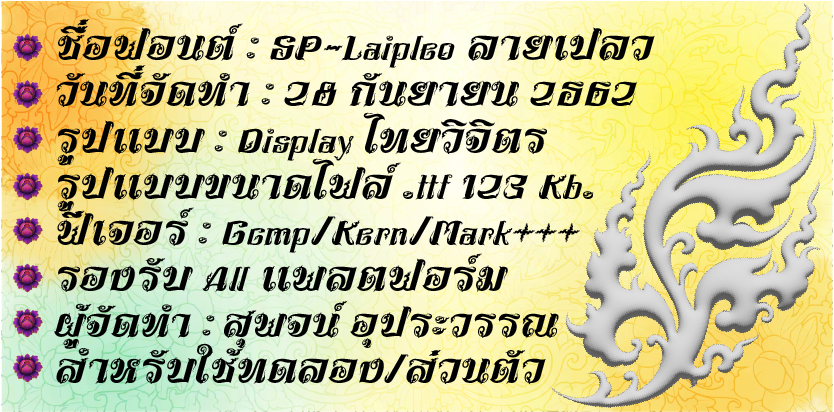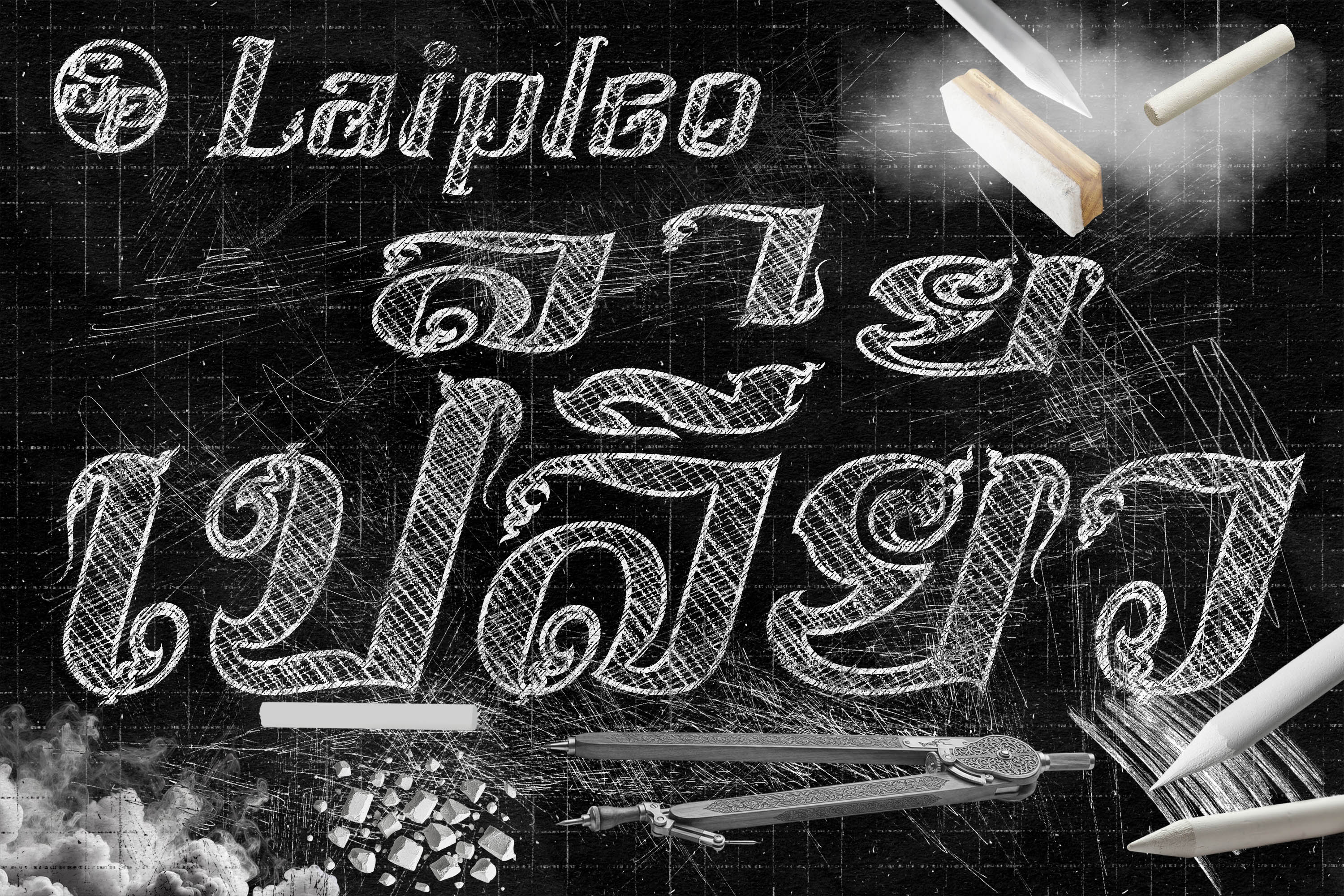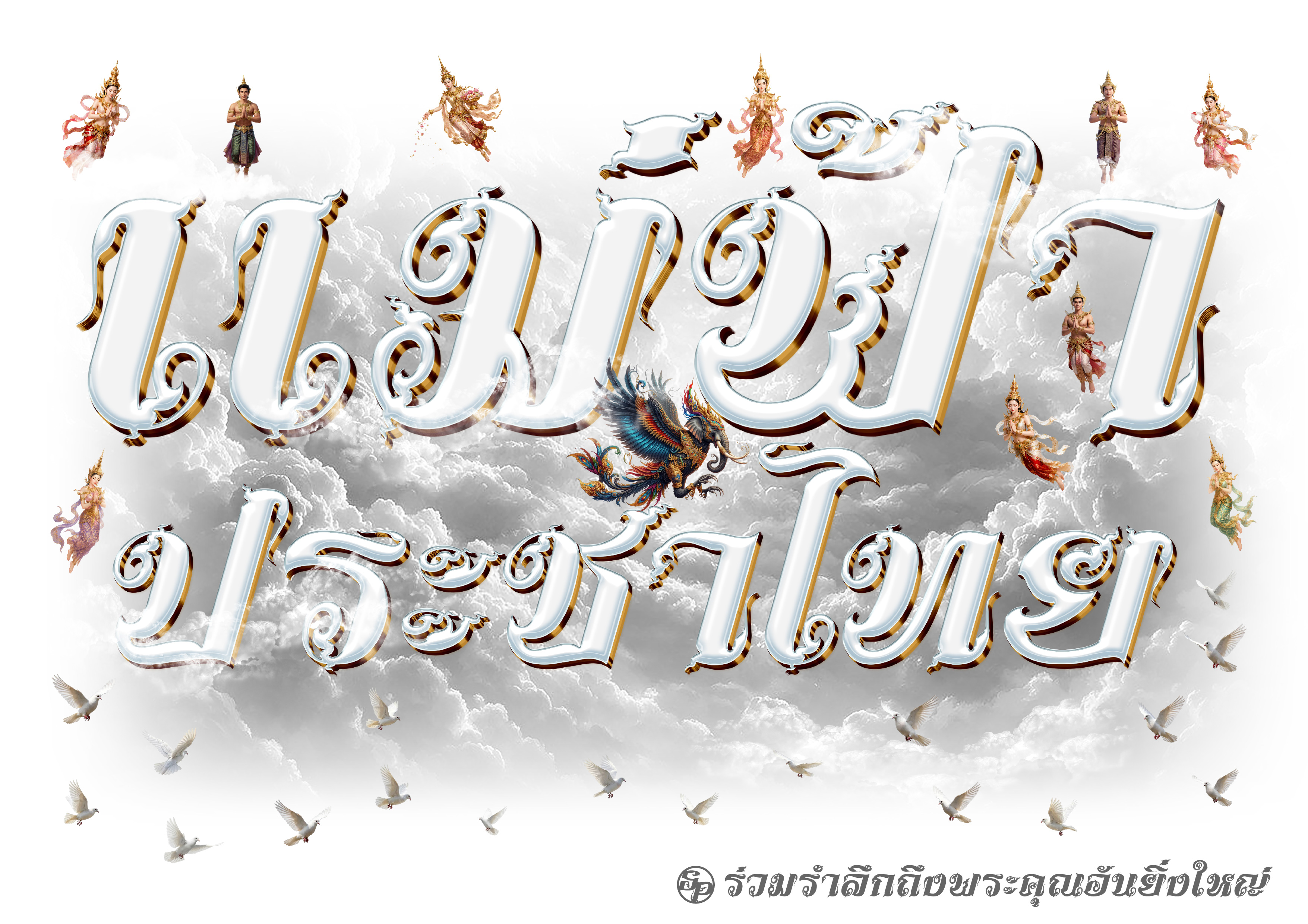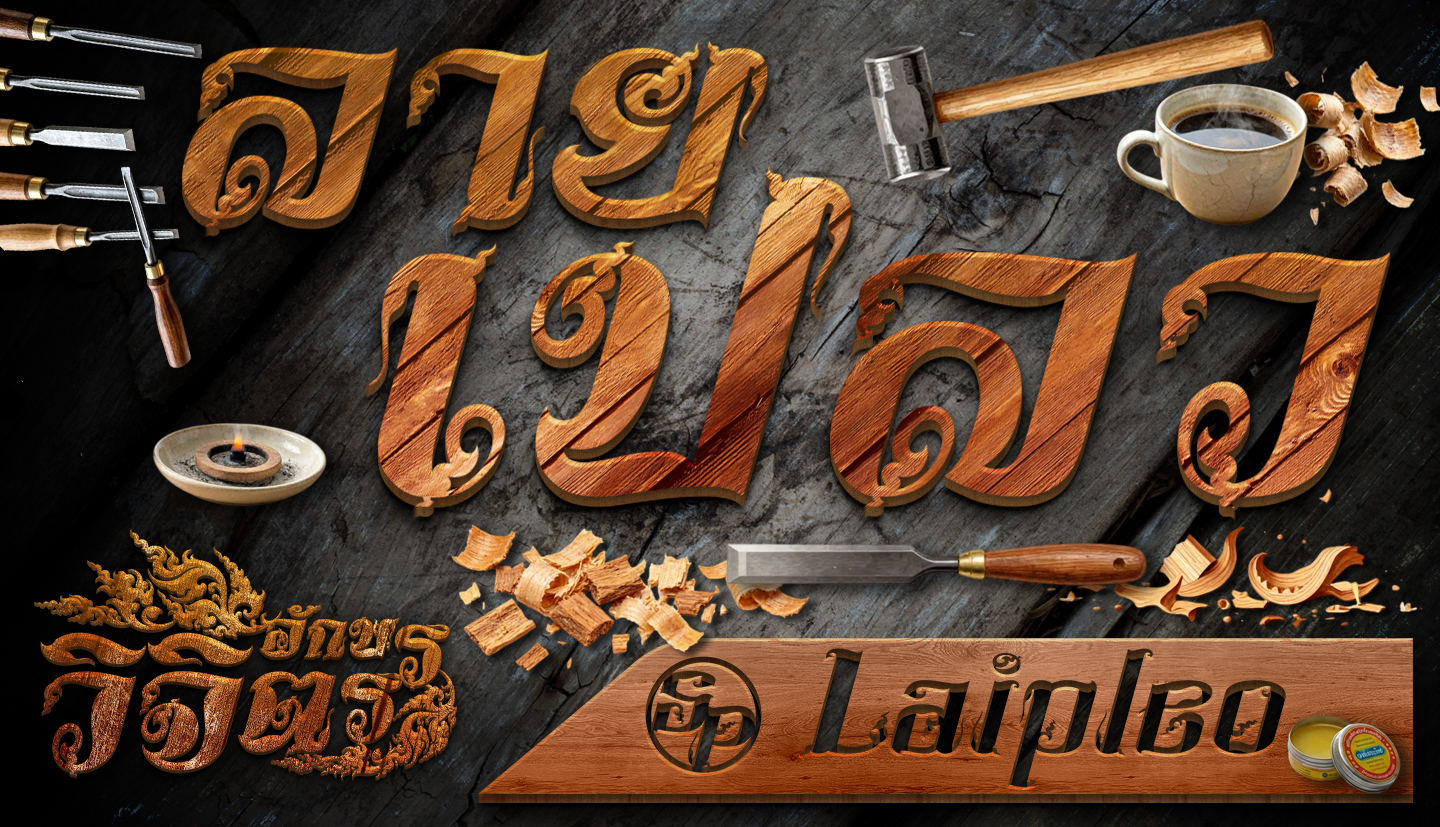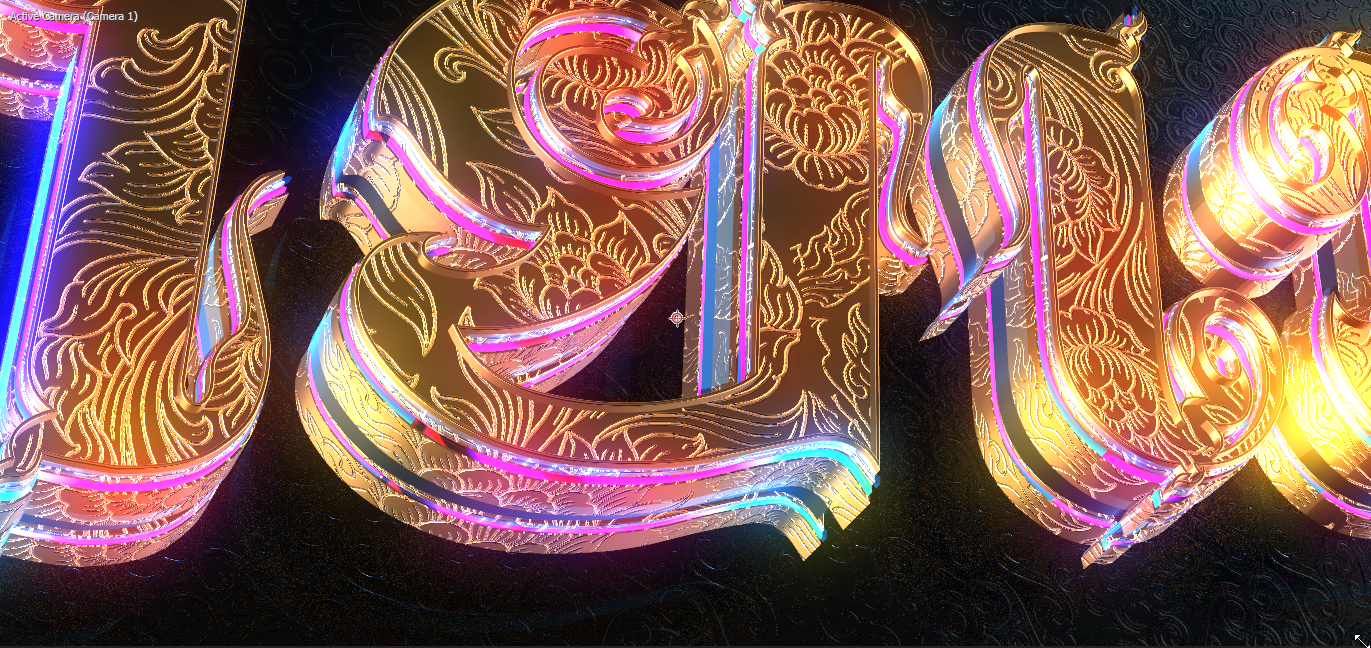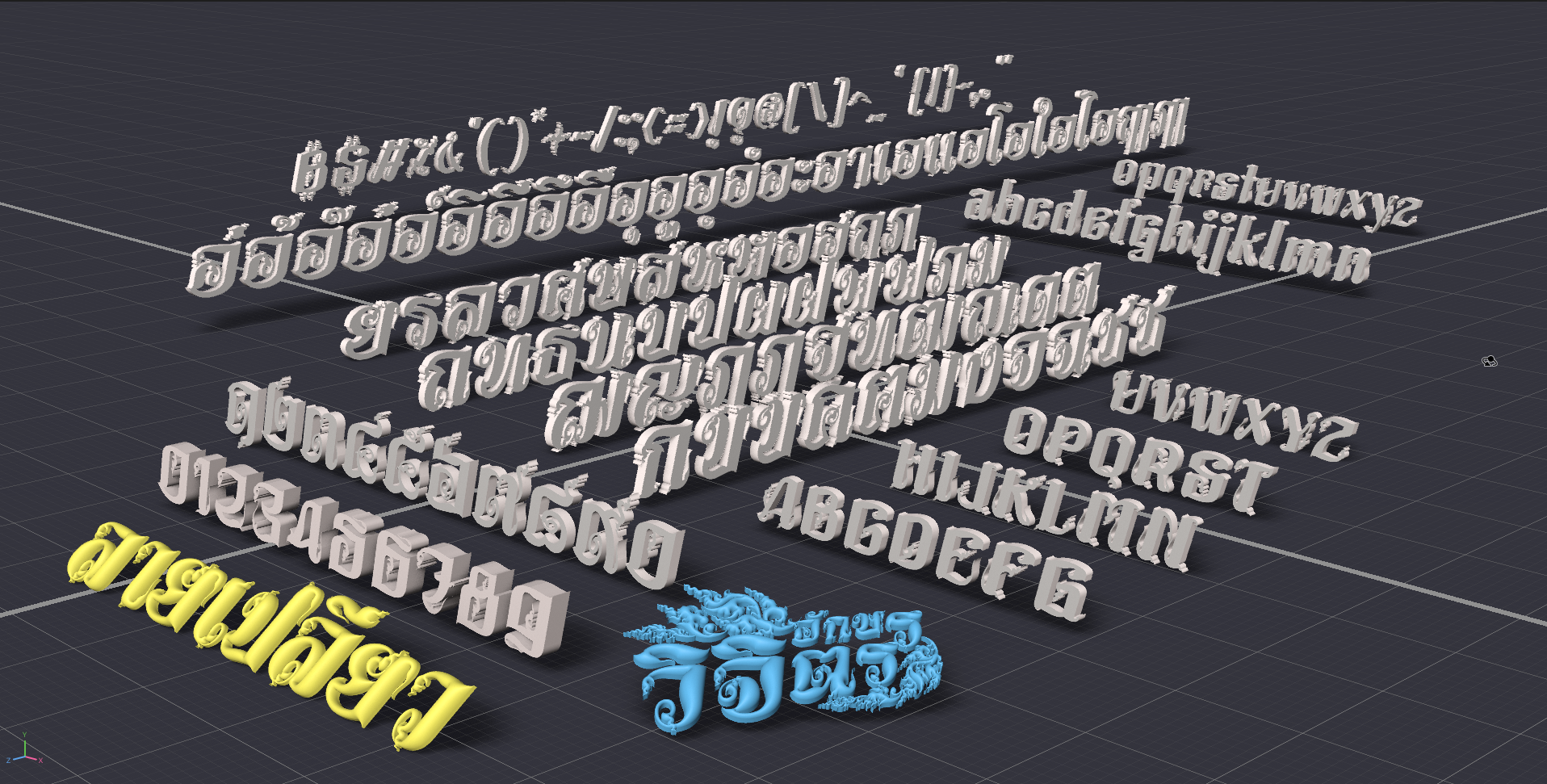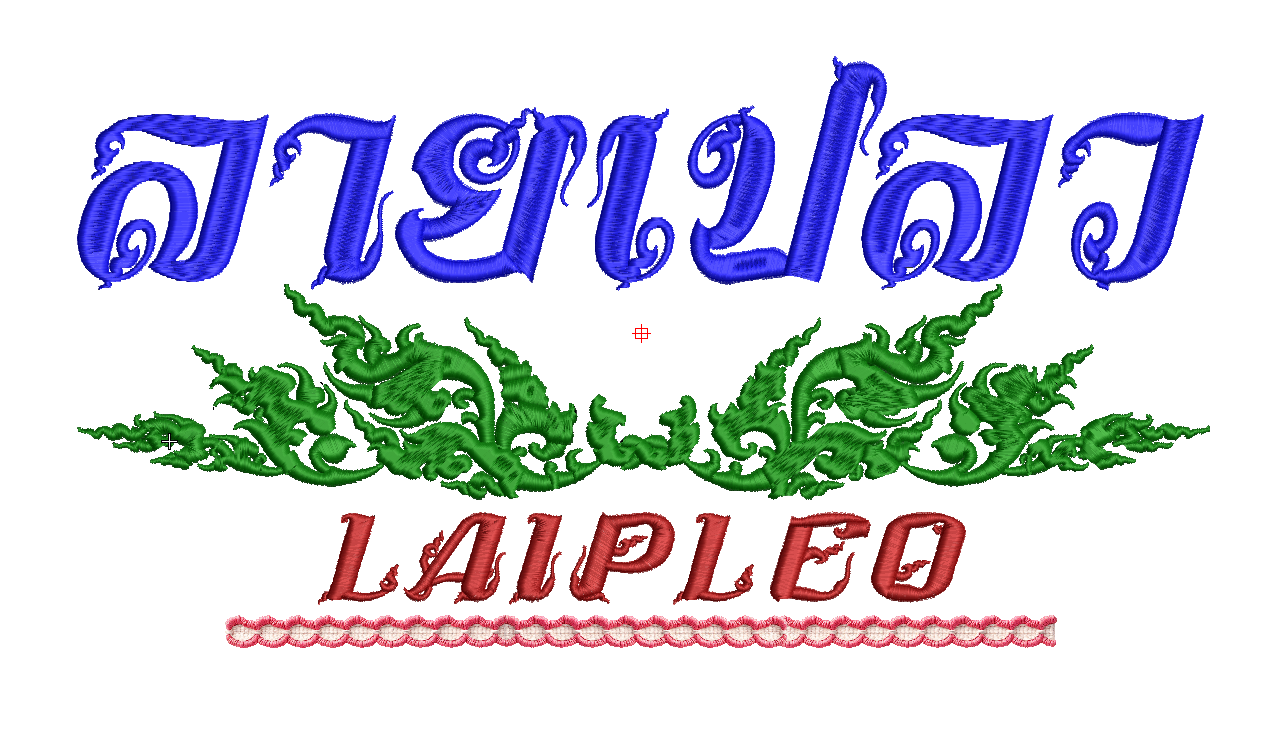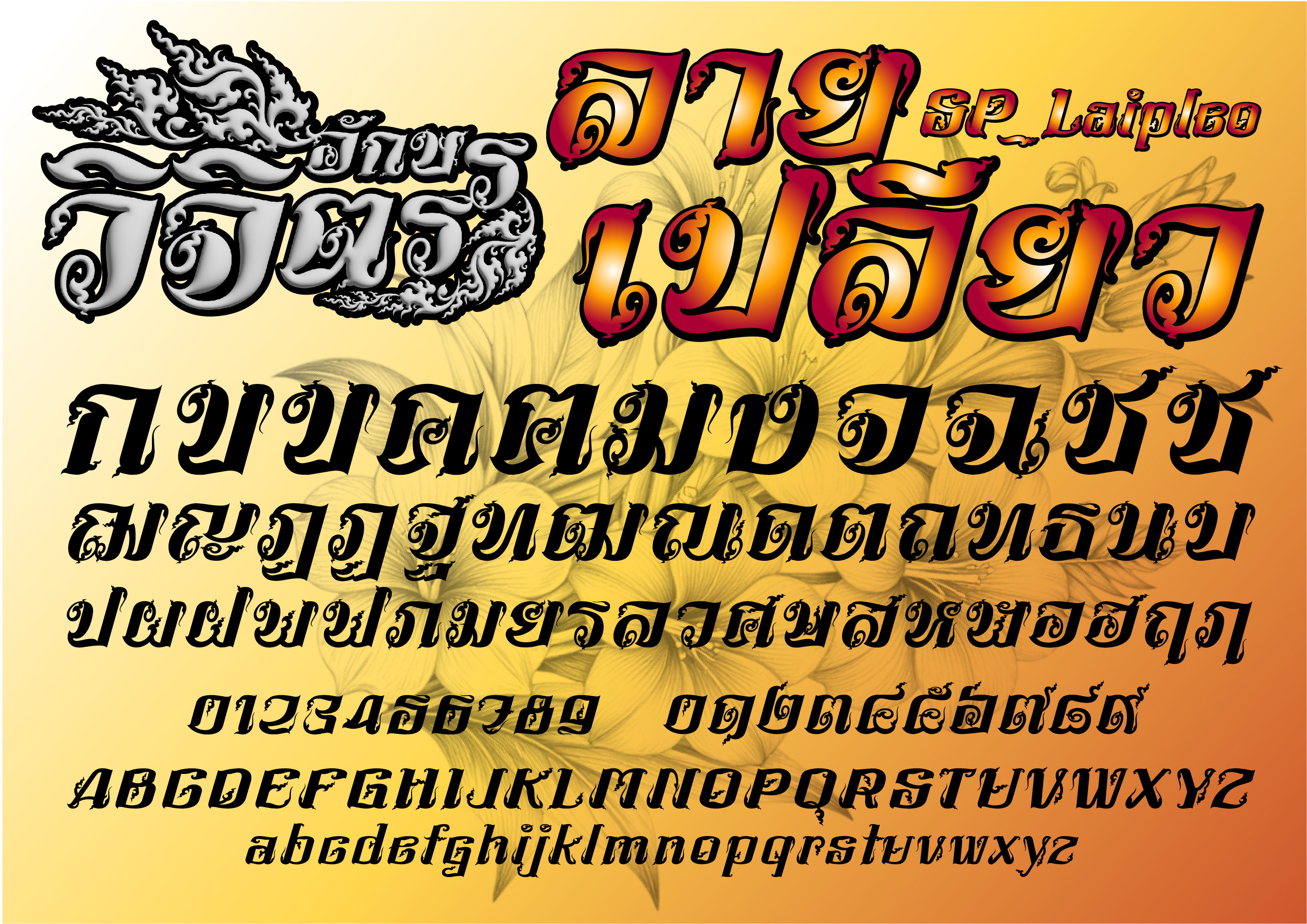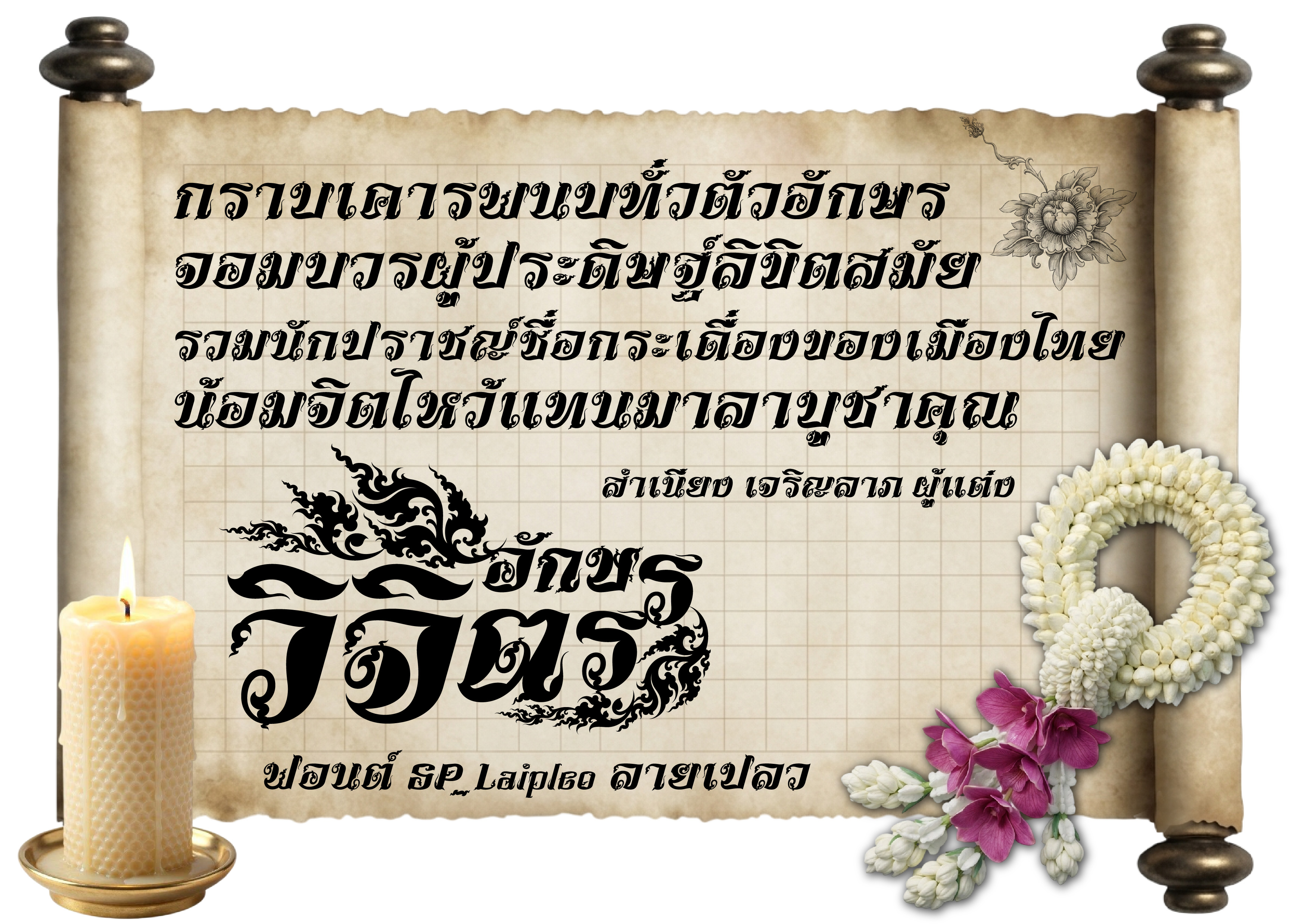
ฟอนต์ SP_Laipleo ลายเปลว
SP_Laipleo ลายเปลว เป็นฟอนต์ในโครงการอักษราสูตรไทยวิจิตร มุ่งเน้นการออกแบบลายเส้นให้กลมกลืนกับศิลปะลวดลายไทย
จัดรูปแบบอักษรให้เป็นเอกลักษณะเฉพาะตัว เข้ากันกับชุดอักษรนั้นๆ รวมถึงอักษรภาษาอังกฤษและสัญลักษณ์อื่นๆครบถ้วนบริบูรณ์
พร้อมทั้งจัดวางฟีเจอร์ (แก้สระลอย-ล็อกเป้าเข้าพิกัด) เพื่อความสวยงามและลงตัว ไม่ว่าจะเป็นช่องไฟ สระวรรณยุกต์ ชั้นล่างชั้นบน
แยกนิคหิตเพื่อการใช้พิมพ์ภาษาบาลีไห้ถูกต้องตามหลักไวยากรณ์ ภายในฟอนต์ๆเดียว (Microsoft-Adobe ต้องเปิดค่ารองรับ)
ฟอนต์อักษรวิจตรชุดนี้ เหมาะสำหรับงานออกแบบเฉพาะด้าน เช่น โลโก้ ป้ายชื่อ สิ่งพิมพ์ โฆษณา งานเทศกาลพิเศษอื่นๆ เป็นอาทิ
ทั้งนี้ยังมีพรีเซนต์ข้อความสไตล์เอฟเฟค ในรูปแบบต่างๆเล็กน้อย เพื่อเป็นแนวทางในการใช้งานฟอนต์ ของผู้สนใจทั่วไปด้วย
SP_FONT อักษรวิจิตร มุ่งเน้นสู่คุณค่าเอกลักษณ์ความเป็นไทย ใส่ใจทุกเส้นสายรายละเอียดศิลป์